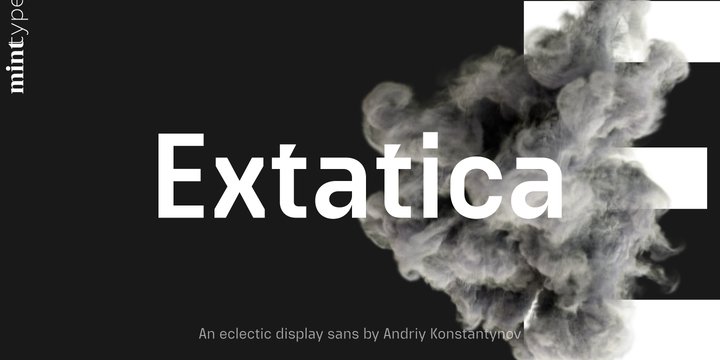
Myfonts Extatica Font
[Myfonts] Extatica Font
Extatica - это эклектичный геометрический дисплей без сериграфического шрифта с узкими капителями.
Он поставляется в 8 весах с соответствующим курсивом, обогащенным несколькими стилистическими чередованиями и функциями OpenType.
Набор глифов включает в себя все европейские языки на основе латиницы, а также основные языки, использующие кириллицу.